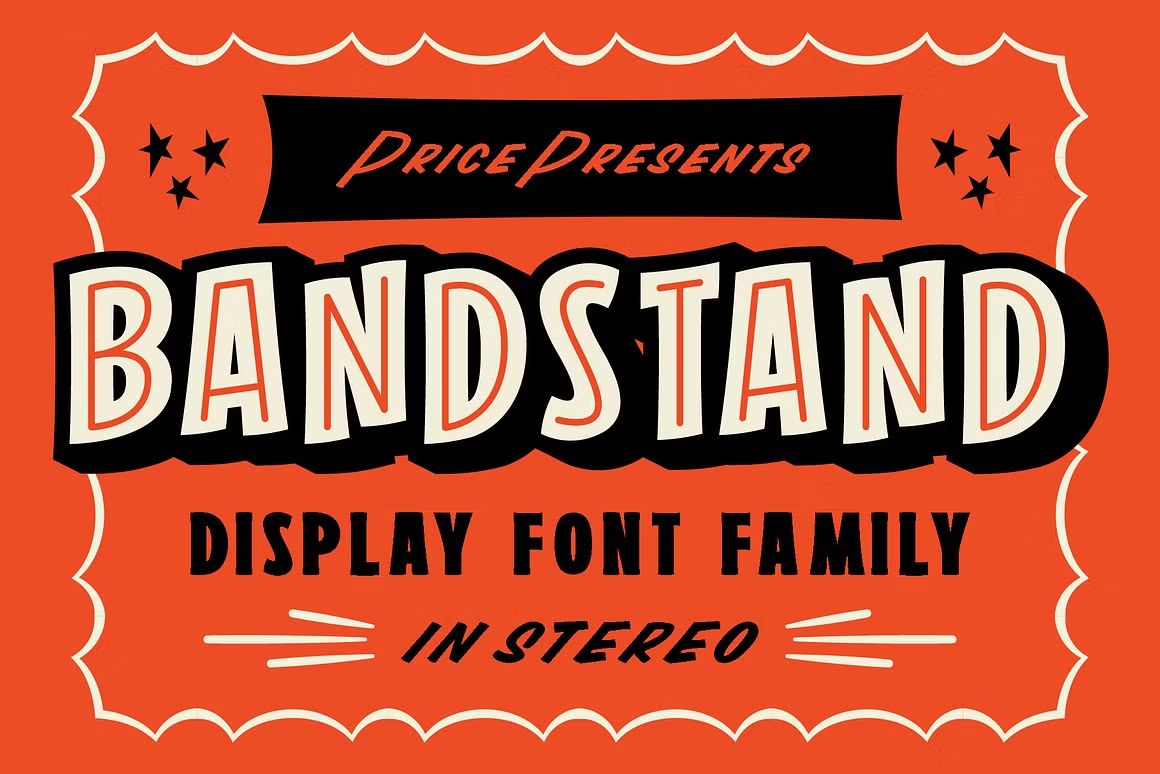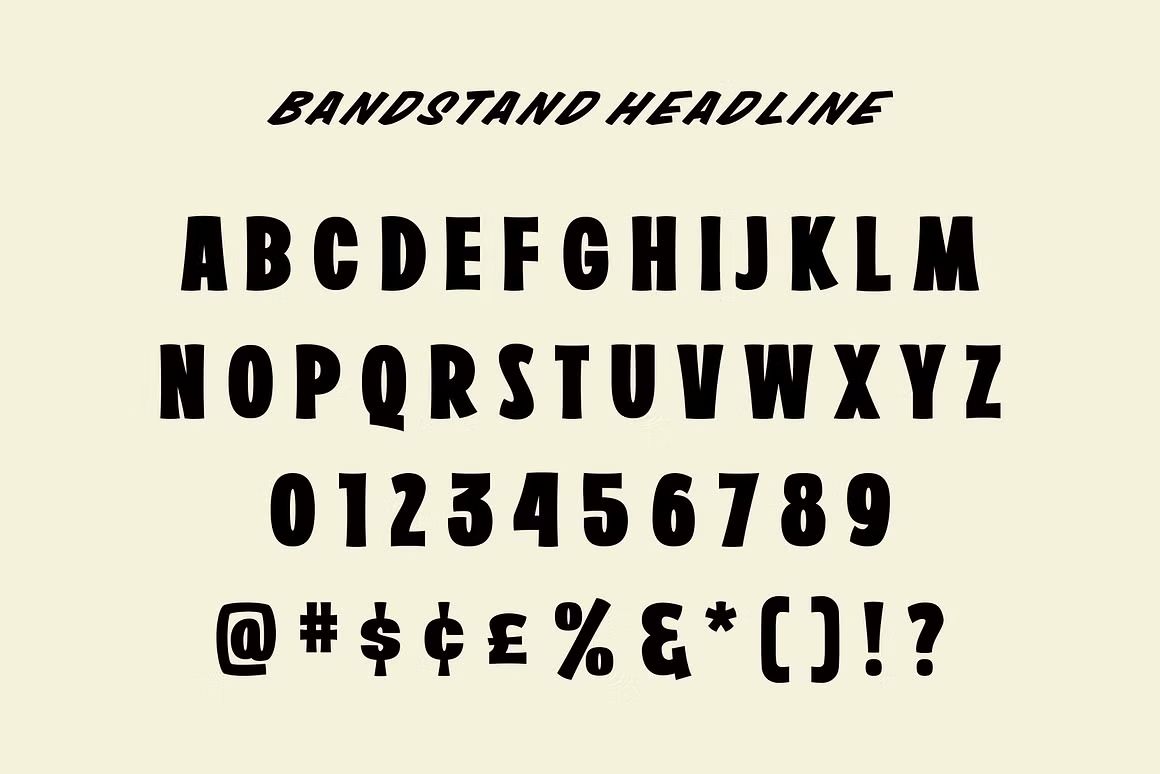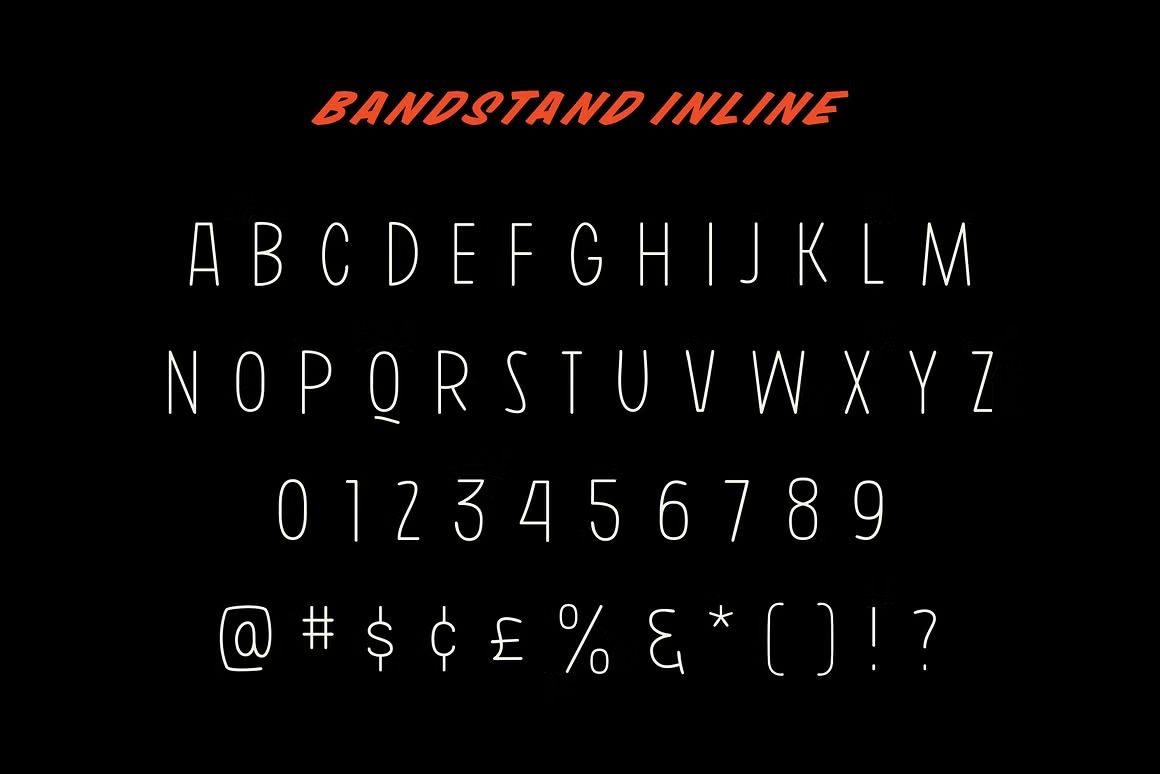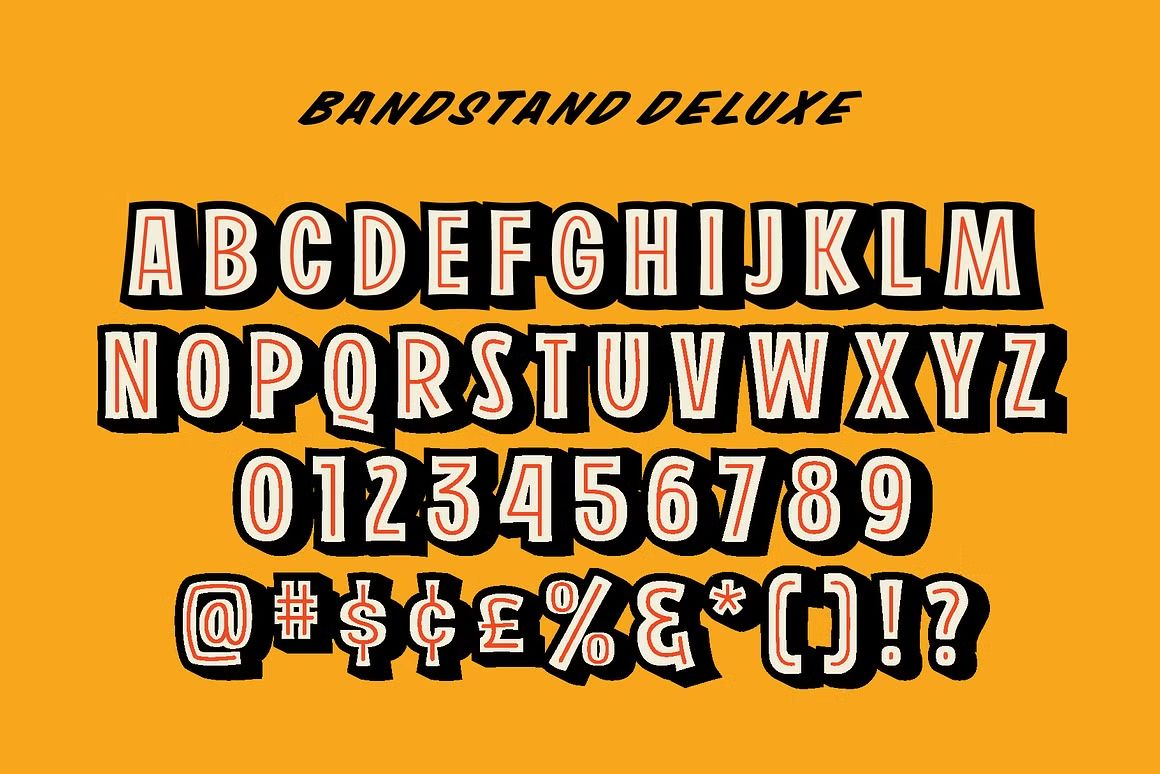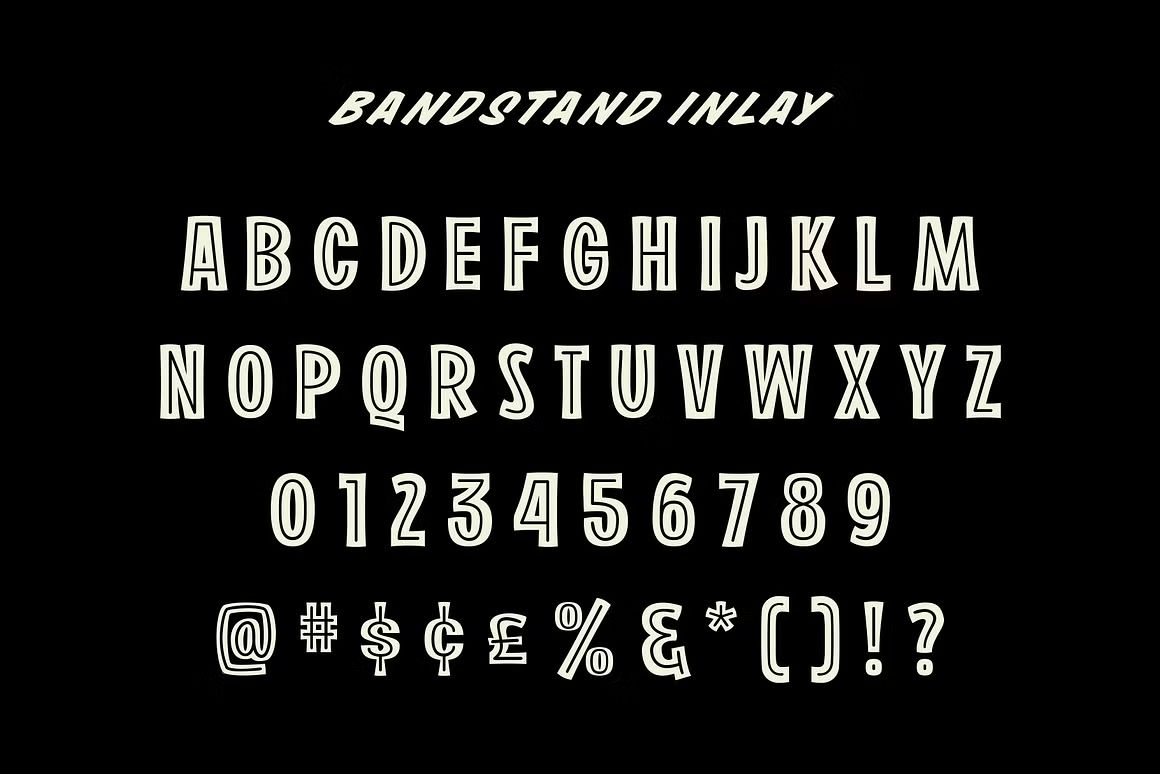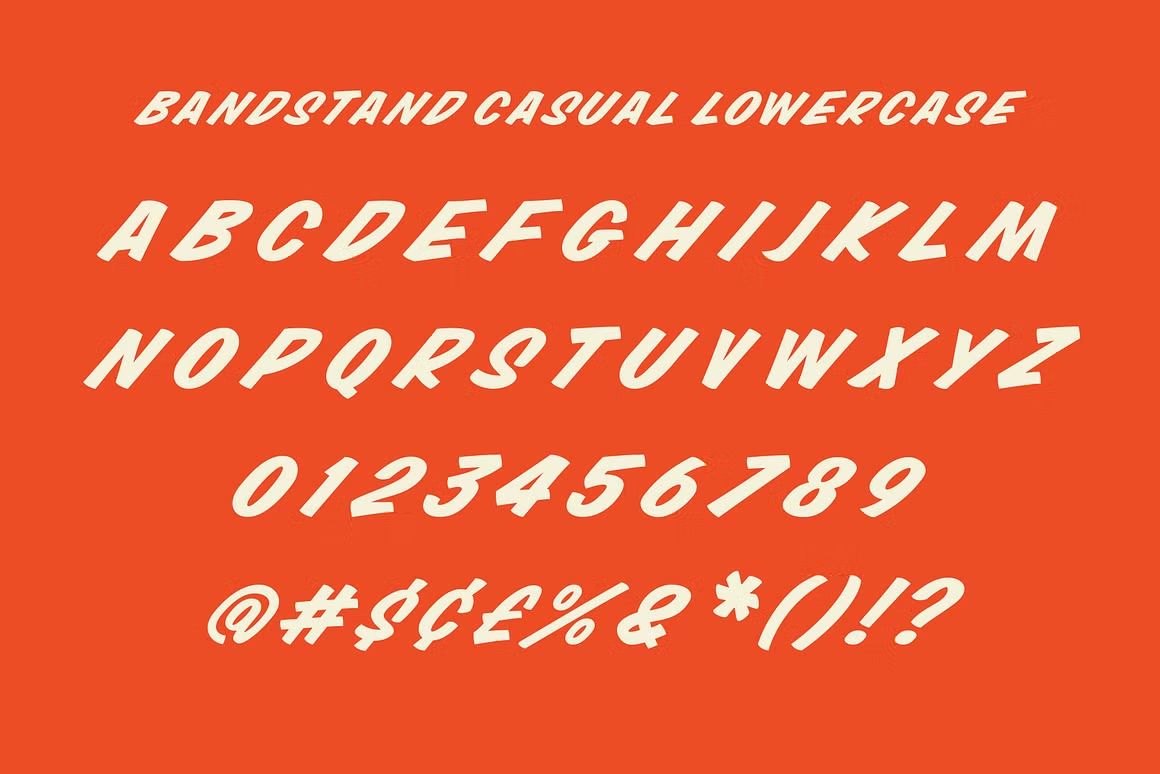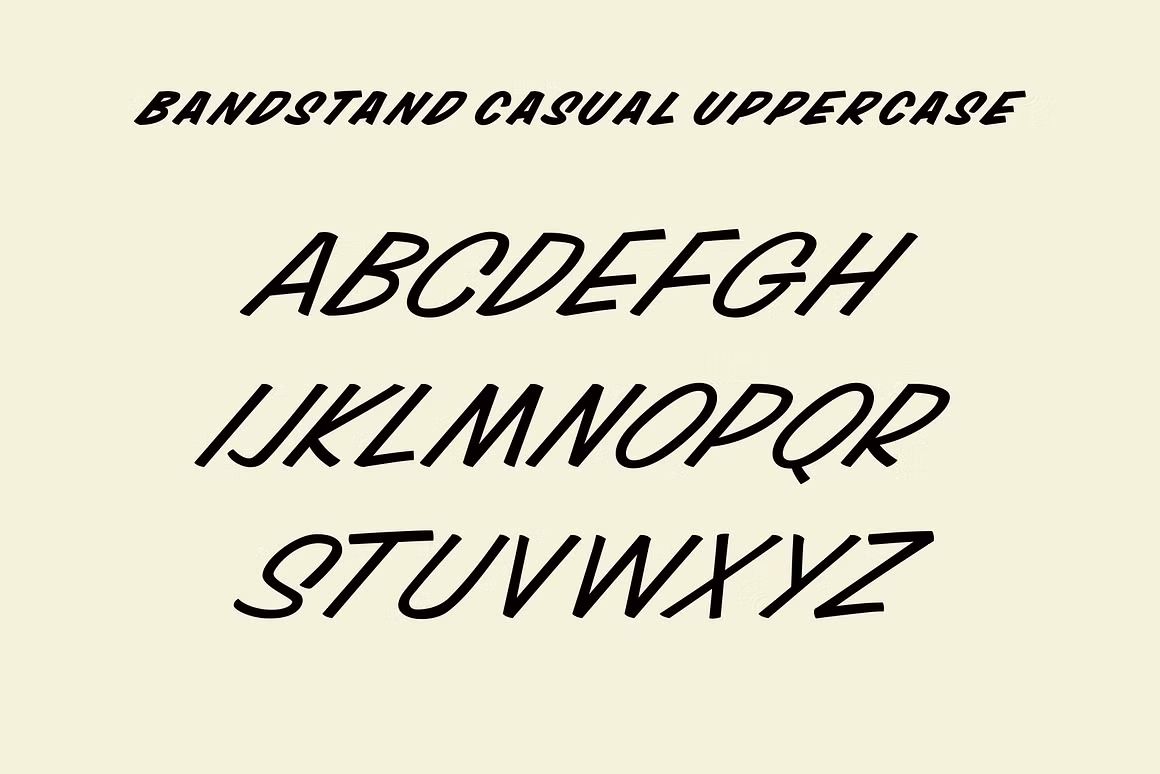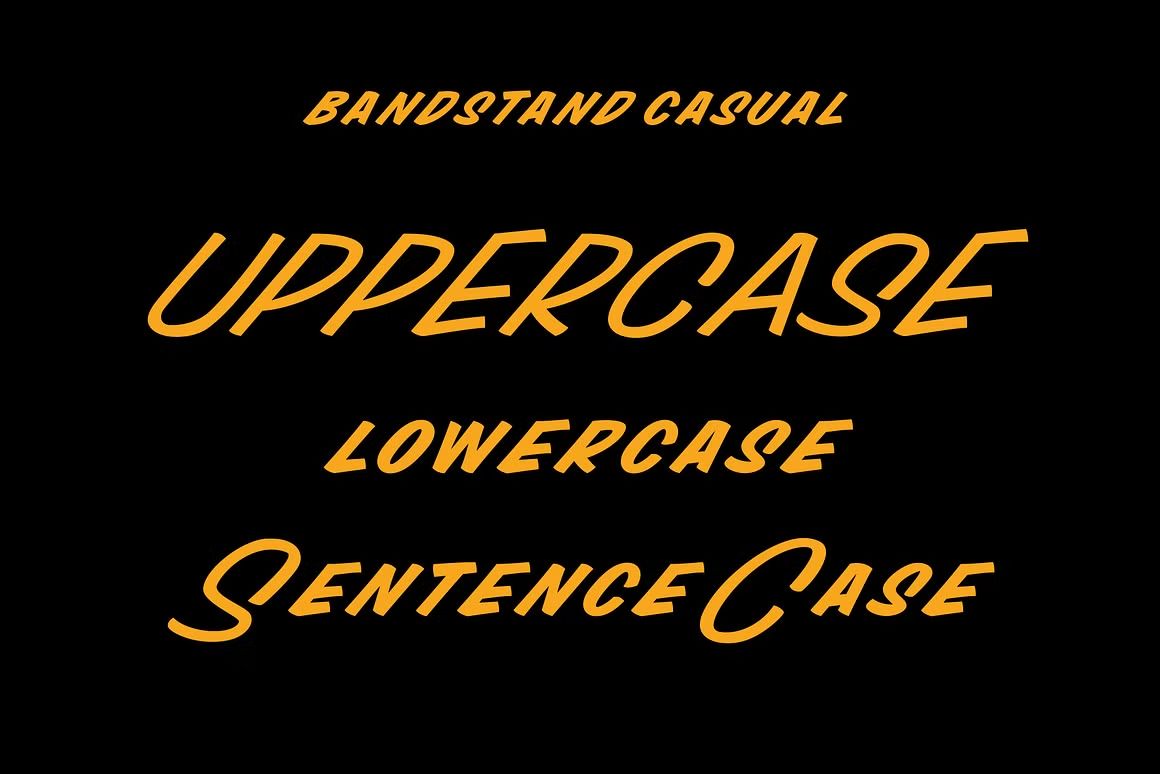
Bandstand – Sans Serif Font
Bandstand adalah font sans serif retro-modern yang tegas dan stylish, cocok untuk poster, logo, dan desain kreatif. Format OTF/TTF/WOFF, siap digunakan.
Bandstand adalah font sans serif dengan gaya retro-modern yang tegas dan berkarakter. Menampilkan bentuk huruf geometris yang sedikit membulat, font ini cocok untuk poster, branding kreatif, kemasan produk, judul editorial, dan desain yang ingin tampil menonjol. Bandstand menghadirkan perpaduan antara kesan vintage dan kontemporer, membuatnya serbaguna untuk berbagai gaya visual.
• Sans serif dengan sentuhan retro dan modern
• Ideal untuk poster, logo, kemasan, dan headline kreatif
• Termasuk huruf besar, kecil, angka, dan simbol